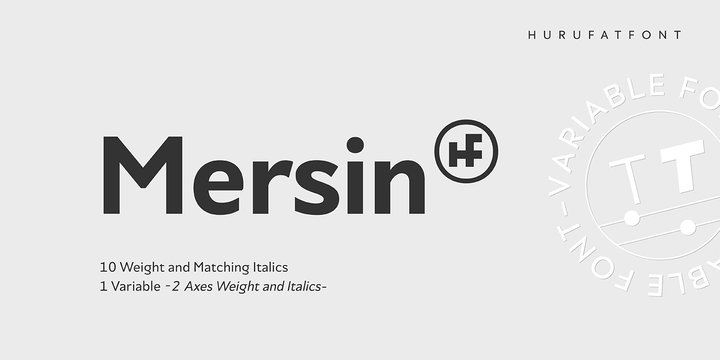
Mersin
- это современный шрифт семейства sans serif. Асимметричная структура начальных и конечных форм таких букв, как "Cc, Ss", является его наиболее отличительной чертой. Mersin состоит из 20 шрифтов, включая 10 весовых начертаний и соответствующие им курсивные начертания. Благодаря 2-осевой (вес и курсив) переменной версии, Mersin предлагает преимущество использования очень богатого веса в диапазоне 100-900. Он включает подробные лигатуры, такие как "Th, Tl, Ti, Tä, Tä, Tü, Tö, iï, fä, fä, fö fü" для очень широких и разнообразных акцентов.
"Mersin Book" и "Mersin Book Italic" специально разработаны для основных текстов и использования мелких шрифтов.
Идеально подходят для фирменного стиля, плакатов, брошюр, указателей и всех других видов графического дизайна.